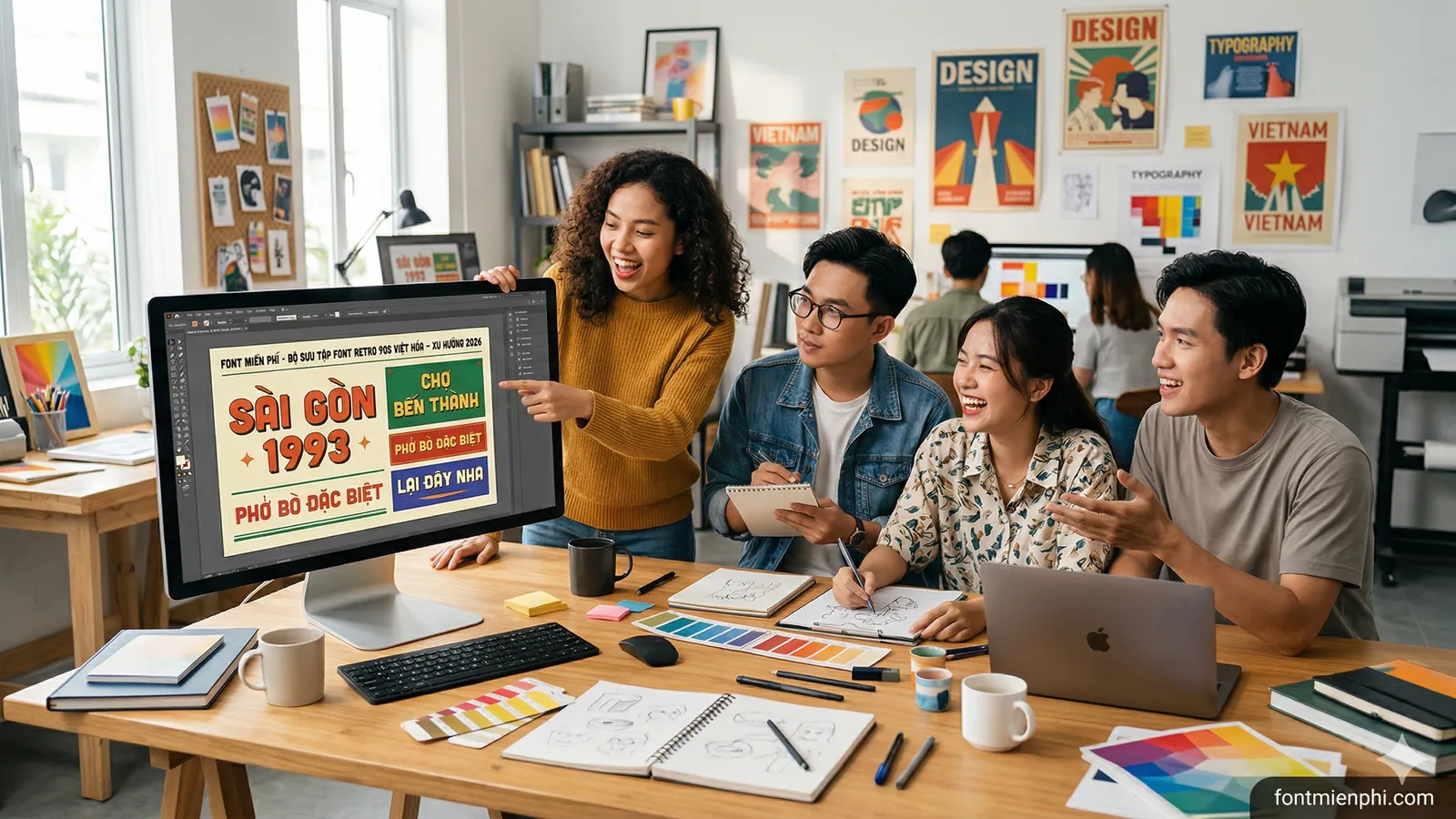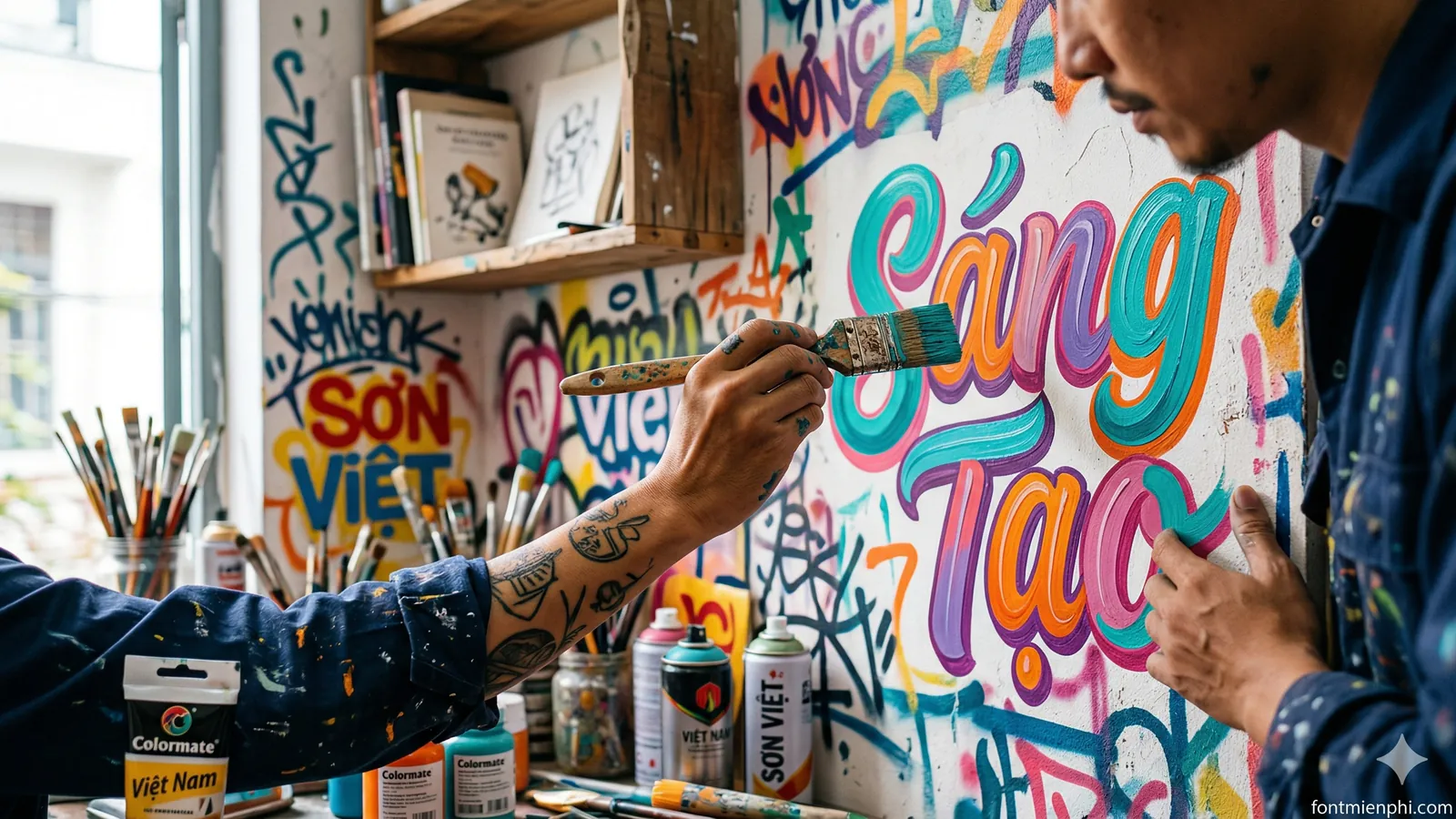
Bài viết này tổng hợp danh sách những bộ font Retro thập niên 90 đã được Việt hóa hoàn chỉnh, đang thống trị xu hướng thiết kế đồ họa năm 2026. Chúng tôi sẽ phân tích chi tiết đặc điểm thẩm mỹ, tính ứng dụng và lý do tại sao phong cách hoài cổ này lại quay trở lại mạnh mẽ, giúp các nhà thiết kế tối ưu hóa trải nghiệm thị giác.
Top Font Retro 90s Việt Hóa Đang Trend Trở Lại Trong Thiết Kế 2026
Sự xoay vòng của thời trang và nghệ thuật đã đưa những giá trị thẩm mỹ của thập niên 90 quay trở lại vị trí trung tâm trong năm 2026. Không còn là những đường nét phẳng tối giản đến đơn điệu, thiết kế hiện nay ưu tiên sự cá tính, rực rỡ và có chút nổi loạn của kỷ nguyên kỹ thuật số sơ khai. Trong đó, nghệ thuật chữ (Typography) đóng vai trò then chốt trong việc tái hiện hơi thở của thời đại này.
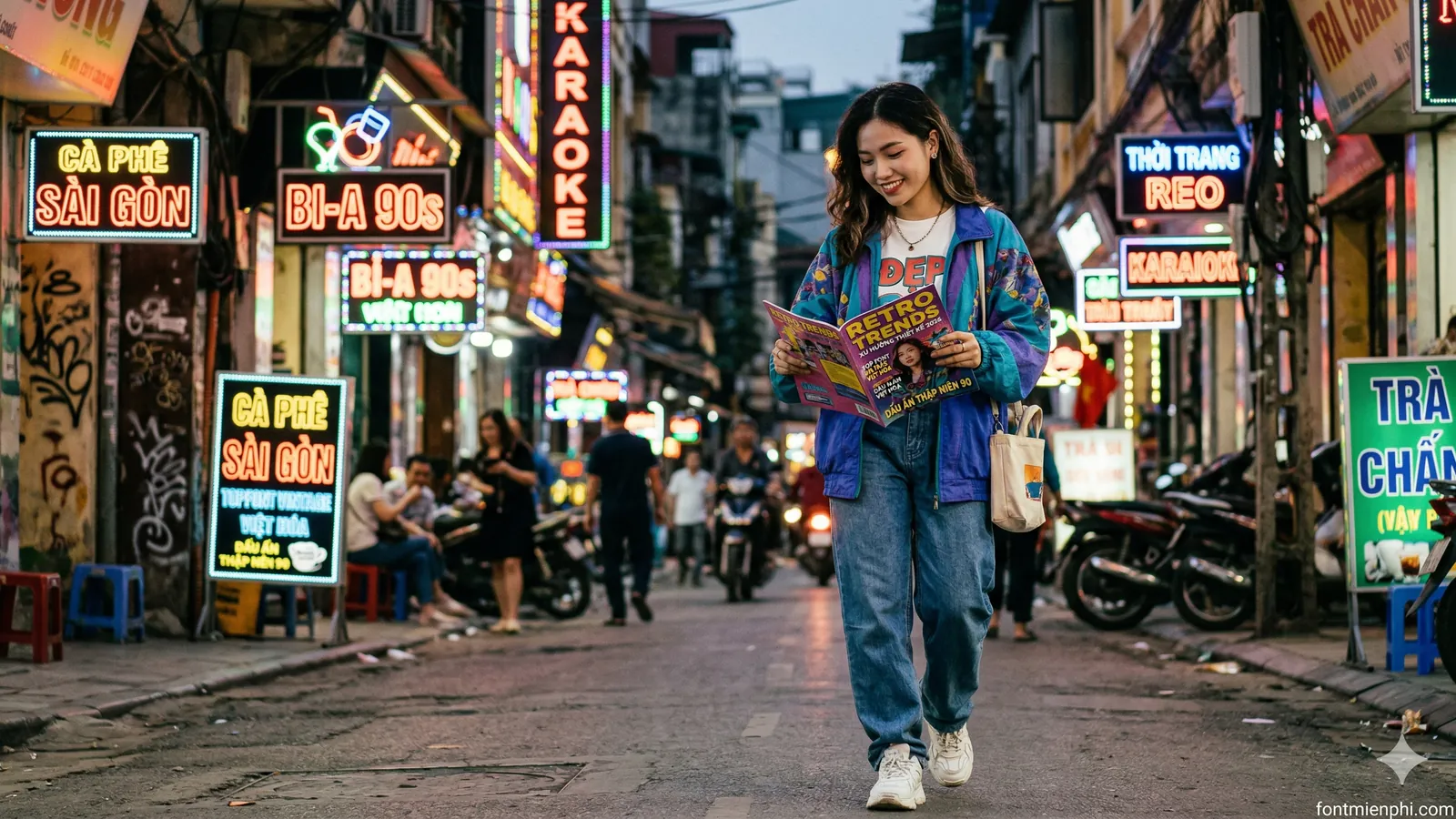
Tại sao phong cách Retro 90s lại bùng nổ trong năm 2026
Thập niên 90 là giai đoạn giao thoa rực rỡ giữa công nghệ analog và sự bắt đầu của kỷ nguyên internet. Những font chữ thời kỳ này mang trong mình sự thô mộc, phá cách nhưng vẫn giữ được nét gần gũi.
Sự bão hòa của phong cách Minimalism
Sau nhiều năm thống trị bởi phong cách tối giản (Minimalism) với các font không chân (Sans-serif) mảnh mai, người xem bắt đầu cảm thấy thiếu đi sự kết nối cảm xúc. Những font chữ Retro 90s với đường nét dày, đổ bóng đổ khối và màu sắc tương phản cao mang lại cảm giác ấm áp, có chiều sâu lịch sử và kích thích thị giác mạnh mẽ hơn.
Làn sóng Nostalgia từ thế hệ Gen Z và Alpha
Năm 2026, thế hệ Alpha bắt đầu định hình phong cách tiêu dùng mới, trong khi Gen Z chiếm lĩnh lực lượng lao động sáng tạo. Cả hai thế hệ này đều có sự say mê đặc biệt với những giá trị cũ nhưng được làm mới (Neo-Retro). Cảm giác hoài niệm về một thời kỳ rực rỡ của các trò chơi điện tử 8-bit, băng cassette và văn hóa Pop là nguồn cảm hứng bất tận.
Đặc điểm nhận diện của Font chữ Retro 90s
Để lựa chọn đúng font chữ cho dự án, bạn cần hiểu rõ những đặc trưng cấu thành nên linh hồn của phong cách 90s.
Đường nét dày và đậm (Bold & Chunky): Hầu hết các font này có trọng lượng chữ rất lớn, tạo sự vững chãi và gây ấn tượng ngay lập tức.
Hiệu ứng đổ bóng và viền (Shadow & Outline): Việc sử dụng các lớp bóng đổ cứng hoặc viền kép là dấu ấn không thể nhầm lẫn.
Màu sắc rực rỡ (Vibrant Colors): Các tông màu neon, pastel đậm hoặc phối hợp tương phản cực mạnh thường đi kèm với các bộ font này.
Hình khối hình học (Geometric Shapes): Sự kết hợp giữa các đường cong mềm mại và các góc cạnh sắc sảo của hình học sơ khai.
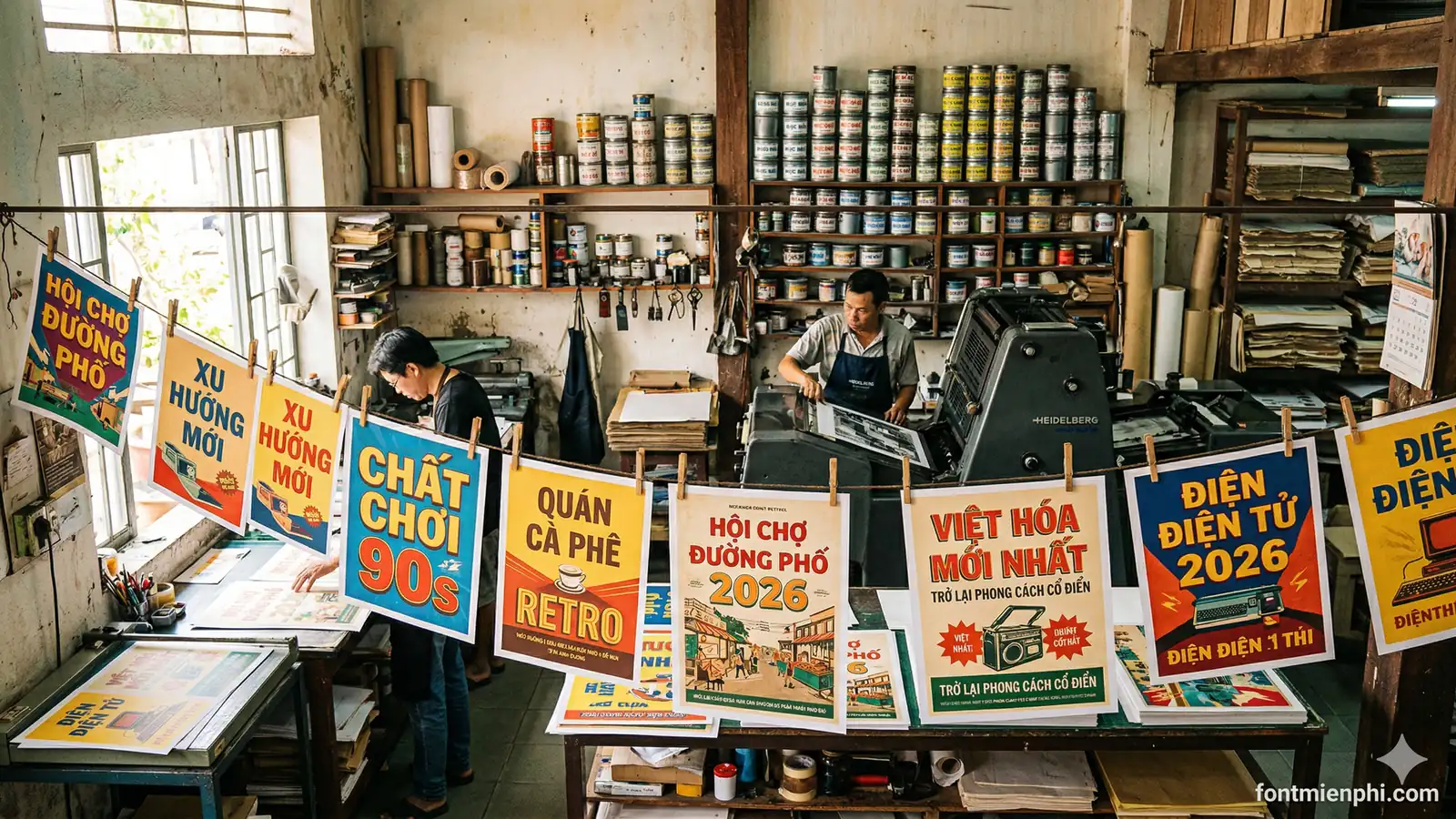
Danh sách Font Retro 90s Việt hóa hàng đầu cho năm 2026
Dưới đây là những bộ font đã được các designer Việt hóa kỹ lưỡng, hỗ trợ đầy đủ dấu tiếng Việt mà không làm mất đi cấu trúc gốc của chữ.
1. Font Bauzian Việt hóa
Bauzian mang đậm phong cách của các tạp chí thời trang và âm nhạc cuối những năm 90. Đây là sự kết hợp hoàn hảo giữa nét cổ điển và sự sang trọng hiện đại.
Đặc điểm: Chữ cái có độ tương phản cao giữa nét thanh và nét đậm. Các đường cong được xử lý mượt mà, gợi nhớ đến các logo của các thương hiệu cao cấp thời kỳ đó.
Ứng dụng: Phù hợp cho tiêu đề tạp chí, bao bì mỹ phẩm cao cấp hoặc các poster sự kiện âm nhạc Retro.
2. Font VCR OSD Mono Việt hóa
Nếu bạn muốn tái hiện giao diện của những cuốn băng video VHS hay màn hình máy tính đời đầu, VCR OSD Mono là lựa chọn không thể thay thế.
Đặc điểm: Đây là dạng font pixel mô phỏng lại các ký tự hiển thị trên màn hình máy quay phim cũ. Nét chữ có phần thô cứng nhưng cực kỳ cá tính.
Ứng dụng: Thiết kế áo thun, làm nội dung cho video ngắn trên mạng xã hội, hoặc tạo hiệu ứng glitch cho website.
3. Font Thunder Việt hóa
Thunder là một font chữ dạng nén (Condensed) mạnh mẽ, mang hơi hướng của các poster phim hành động và quảng cáo đường phố thập niên 90.
Đặc điểm: Chiều cao chữ lớn, bề ngang hẹp, tạo cảm giác uy lực và chiếm lĩnh không gian. Khi được Việt hóa, các dấu thanh được đặt tinh tế để không làm phá vỡ cấu trúc nén của font.
Ứng dụng: Tiêu đề lớn (Headline), thiết kế banner quảng cáo ngoài trời, bìa sách nghệ thuật.
4. Font Groovy Việt hóa
Groovy đưa chúng ta trở lại với văn hóa đường phố và sự nổi loạn của những năm 90. Đây là font chữ dạng kịch bản (Script) nhưng mang tính chất đồ họa rất cao.
Đặc điểm: Các đường nét nối liền nhau một cách tự nhiên, tạo cảm giác như được vẽ tay bằng cọ bản lớn. Font có độ dày đồng nhất và rất dễ đọc dù ở khoảng cách xa.
Ứng dụng: Thiết kế logo cho các quán cà phê phong cách Retro, thương hiệu thời trang Streetwear.
5. Font Hernandes Việt hóa
Hernandes là đại diện tiêu biểu cho phong cách Slab Serif (serif chân lớn). Nó mang lại cảm giác tin cậy nhưng vẫn đầy sự phá cách.
Đặc điểm: Chân chữ vuông vức, dày dặn. Khoảng cách giữa các chữ cái được tính toán để tạo nên một khối văn bản đặc khít và ấn tượng.
Ứng dụng: Thiết kế nhận diện thương hiệu cho các ngành nghề liên quan đến thủ công, đồ uống có cồn hoặc các tiệm cắt tóc Barber Shop.
Hãy thử nghiệm, kết hợp và thậm chí là phá vỡ các quy tắc để tìm ra phong cách riêng của mình với những bộ font Retro này. Sự sáng tạo không có giới hạn, và những con chữ chính là vũ khí sắc bén nhất để bạn thể hiện bản sắc cá nhân trong thế giới thiết kế đồ họa đầy biến động.